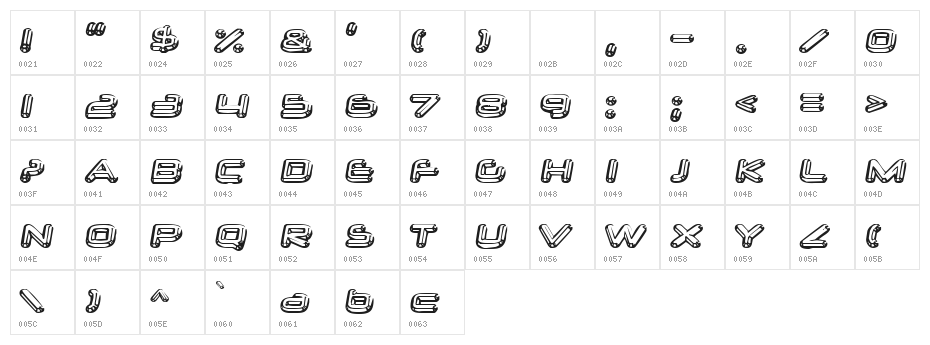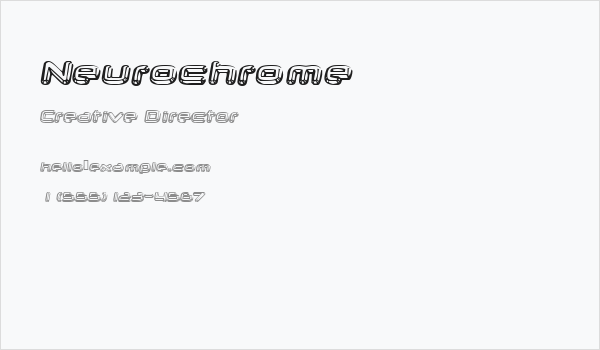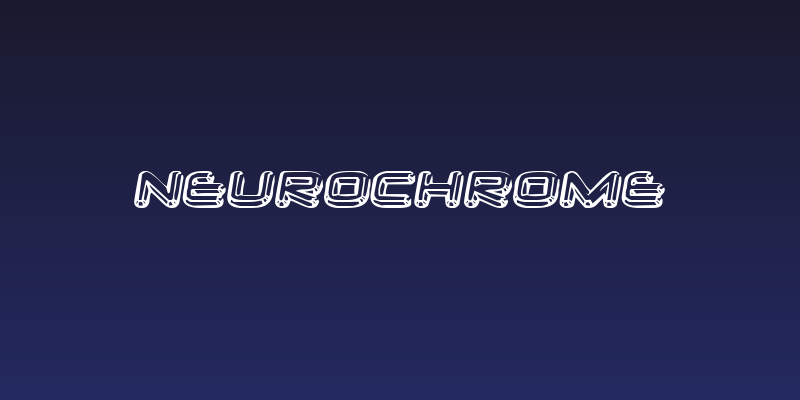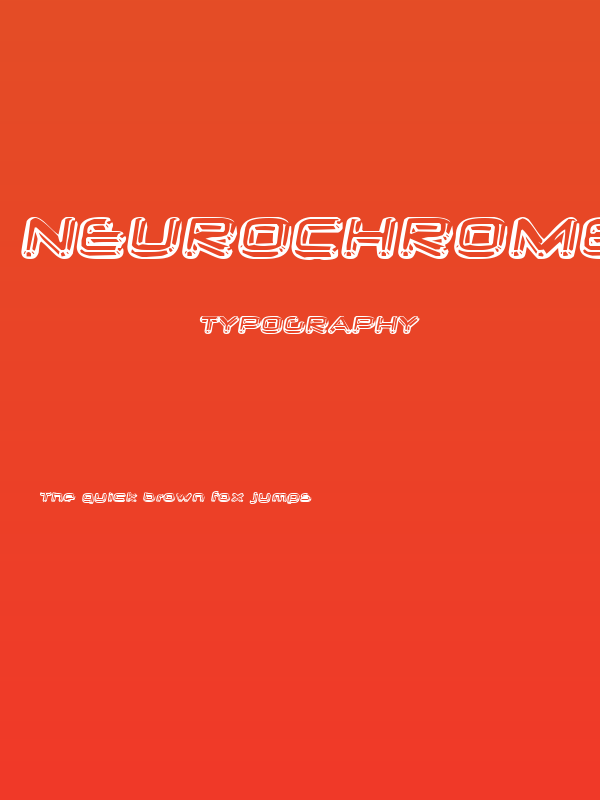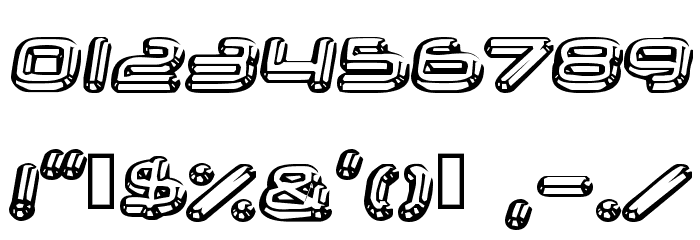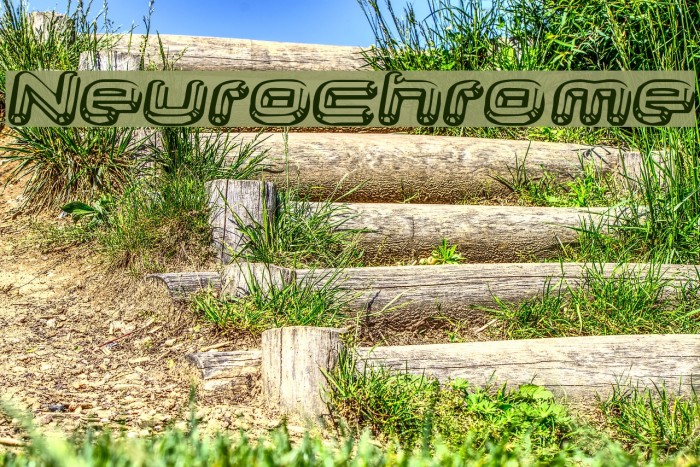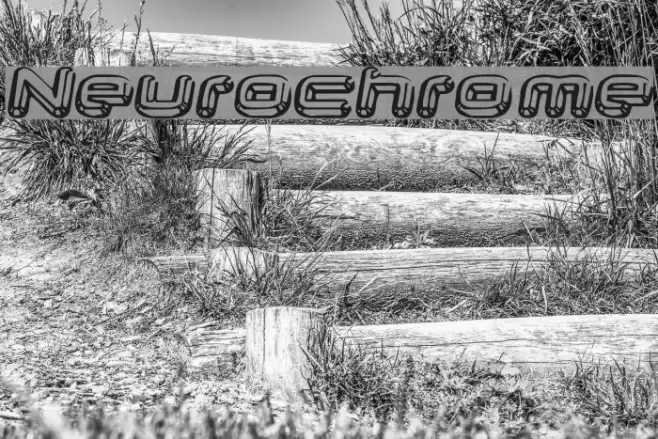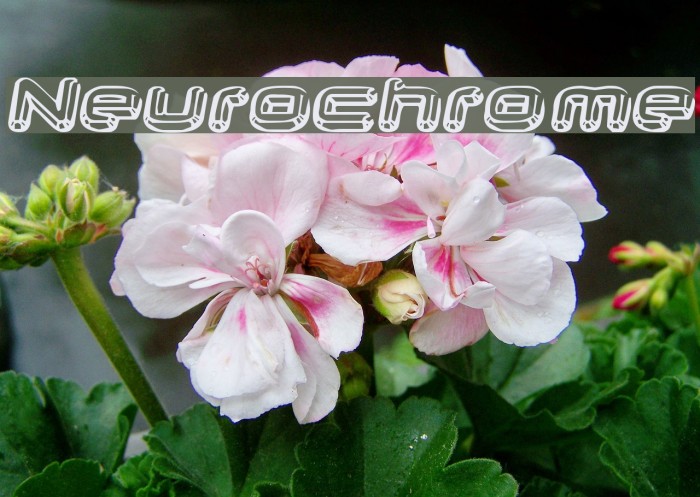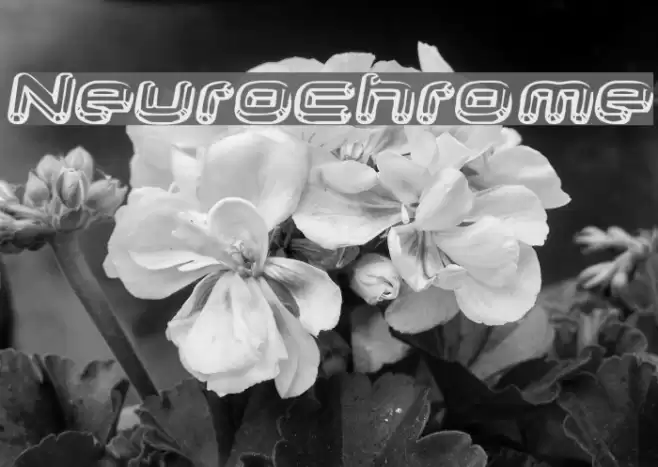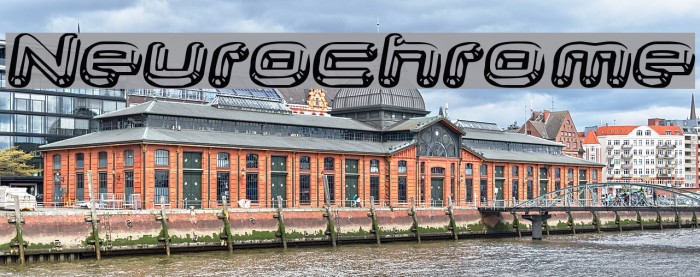
Neurochrome Font
✎ 3D
| Gesamtstil | Futuristic |
| Vorgeschlagene Projekte | Ideal for sci-fi themed posters, video game titles, tech branding, and futuristic event flyers. |